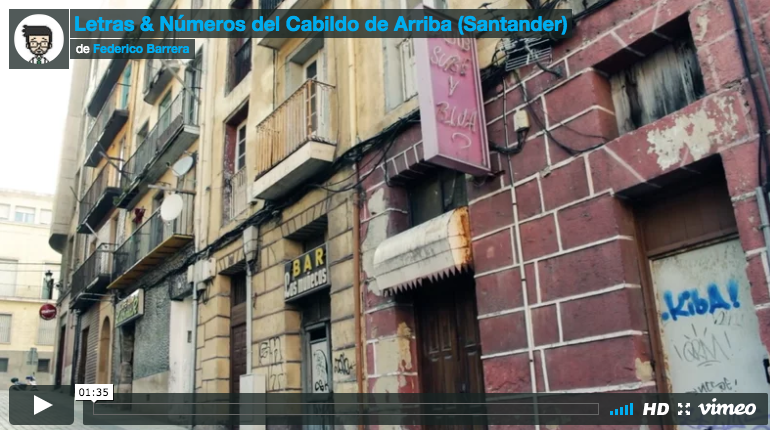
Andando por los rótulos de Madrid (II)
Cada visita express y callejeo a la capital nos descubre esas letras que nos hablan de la Historia de la ciudad desde su comercio local. Sólo hay que mirar hacia arriba.Madrid guarda en sus calles pequeños tesoros tipográficos que aguantan al paso del tiempo. En algunos casos abandonados, en otros integrados dentro de otro negocio distinto, pero casi siempre visibles para disfrute del ojo. Por otro lado, hemos descubierto que desde el ayuntamiento se ha reconocido la importancia de algunos de los comercios centenarios y tienen una placa en el suelo que así lo refleja, todo un ejemplo de puesta en valor, esperemos que en otras ciudades cunda el ejemplo.